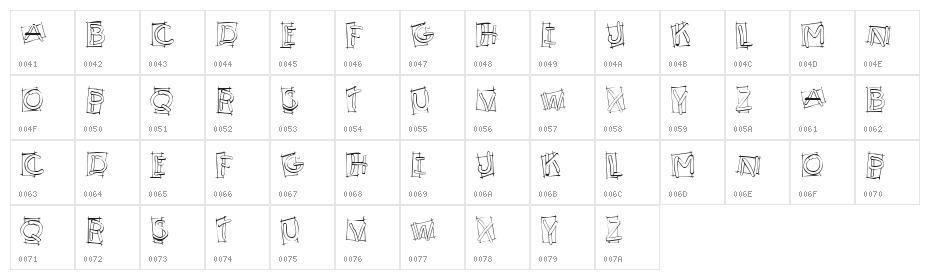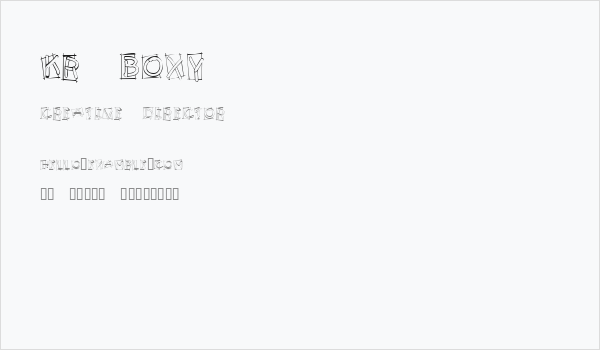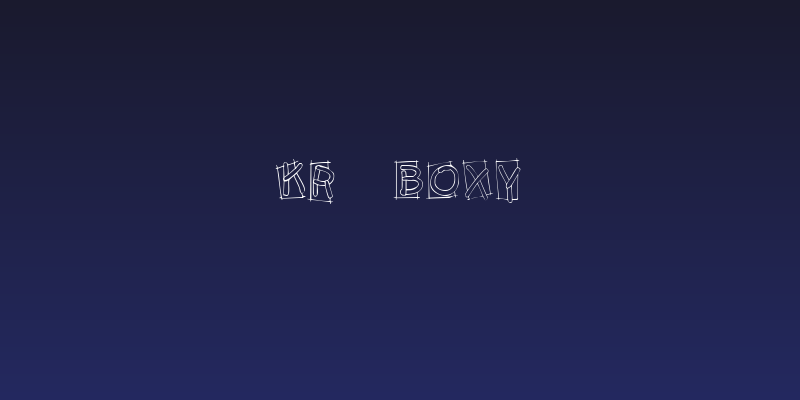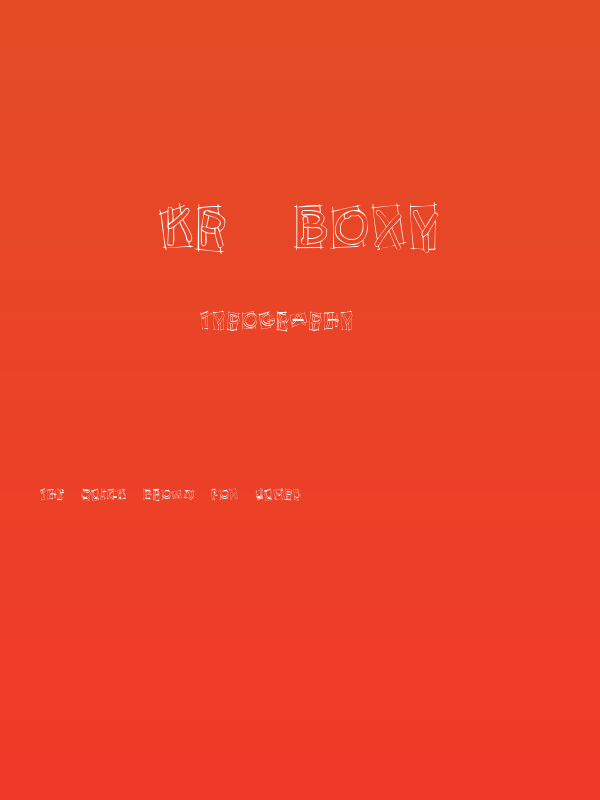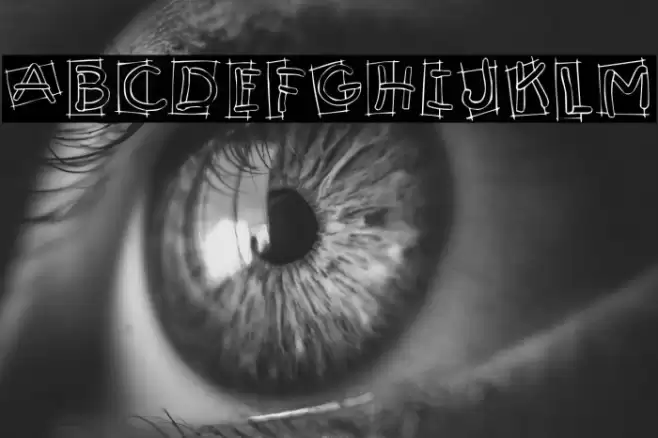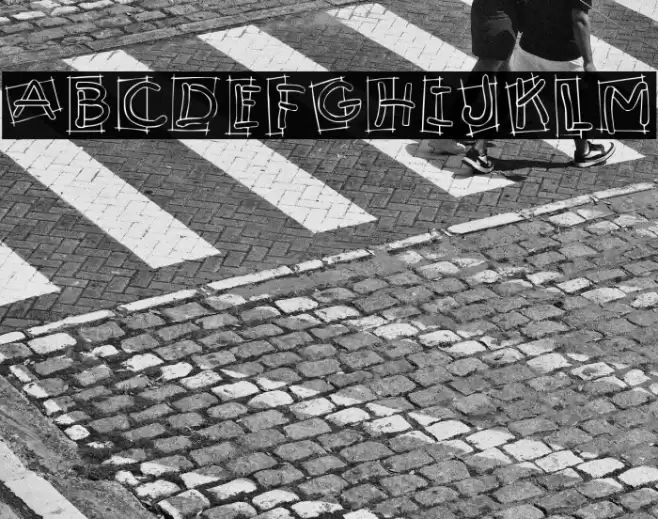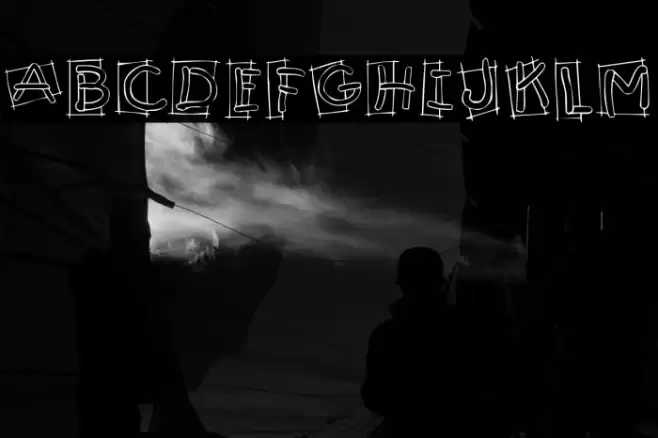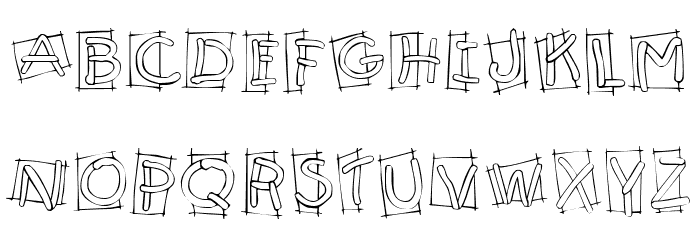
KR Boxy Font
| Caso d'uso | Logos, Posters, Creative projects |
| Progetti proposti | Ideal for creative projects such as children's books, playful branding, artistic posters, and unique invitations. |